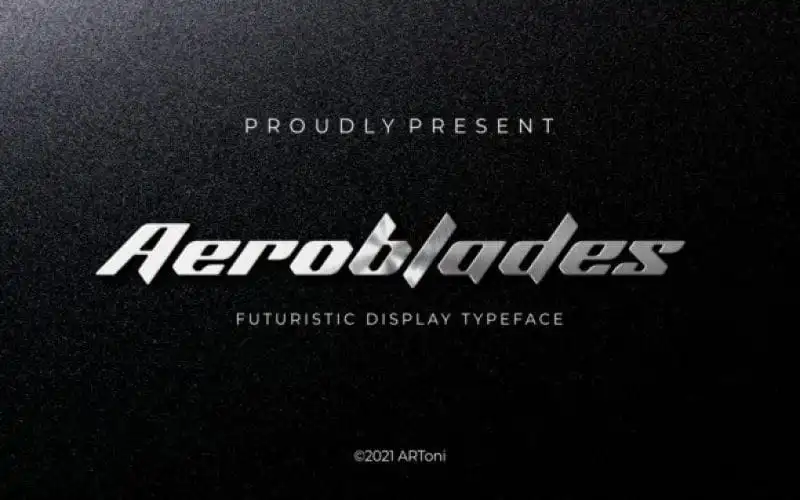
Aeroblade Display Font – Download Grátis
Aeroblade Display Font é uma escolha perfeita para quem busca um estilo inovador e moderno. Com um look futurista, este tipo de fonte oferece uma beleza profissional que se destaca, ideal tanto para criações gráficas como cartazes e headlines quanto para subtítulos e design de logomarcas. Desenvolvida pelo designer ARToni na plataforma 99designs, a Aeroblade Display é perfeita não apenas para dar um toque moderno em mensagens publicitárias, mas também para usar em elementos de marca que querem destacar-se. Seja você uma agência gráfica ou alguém criando seus próprios projetos pessoais, este tipo de fonte se torna uma ótima opção, garantindo um resultado impecável em sua próxima criação visual.